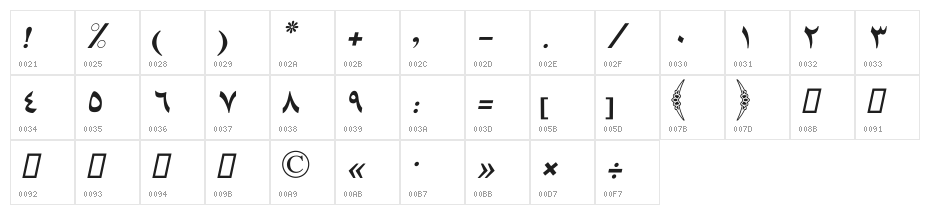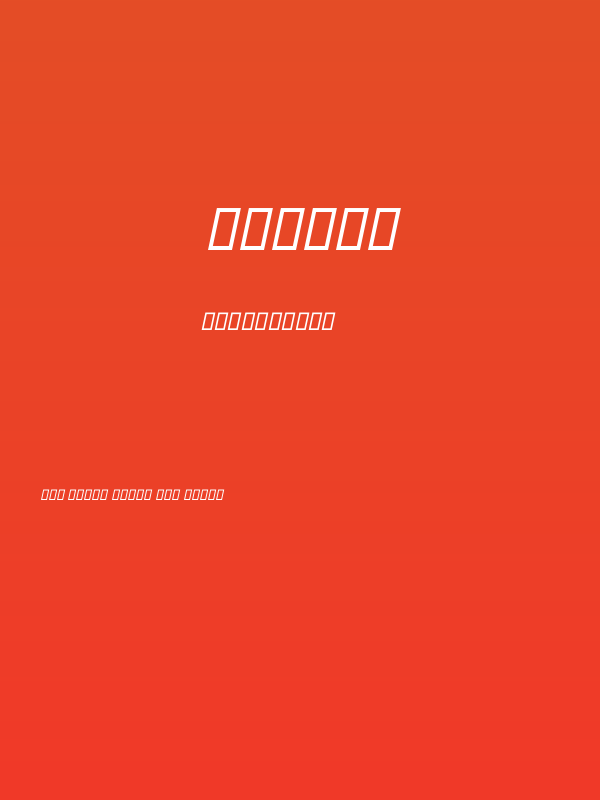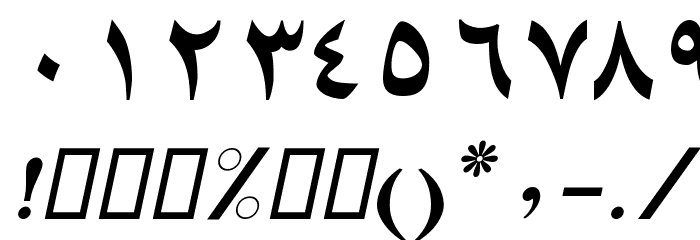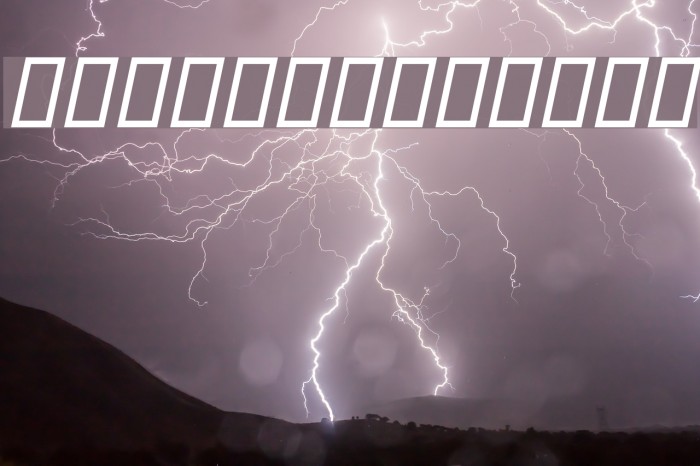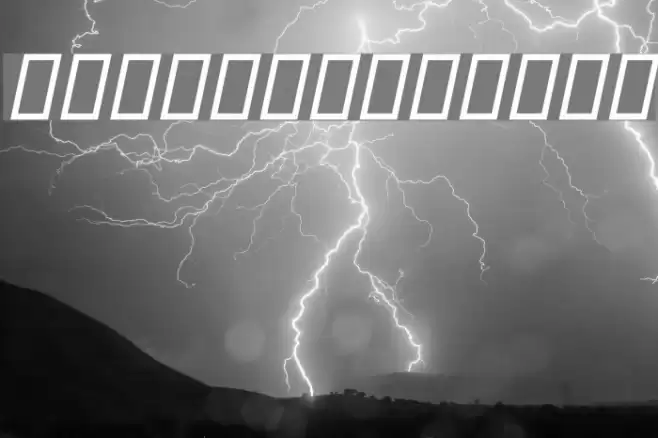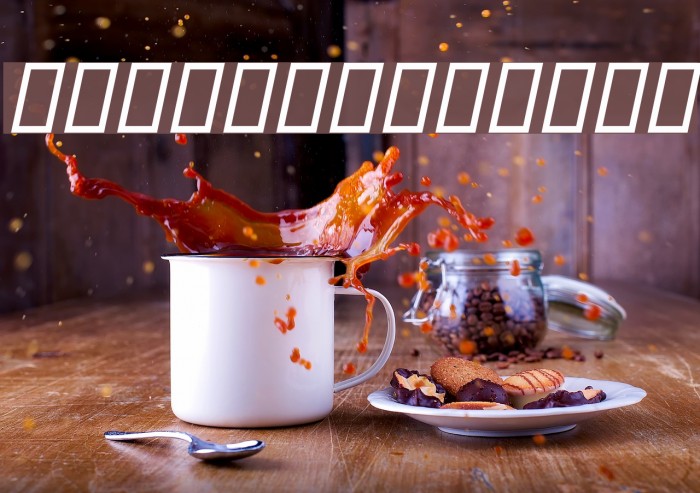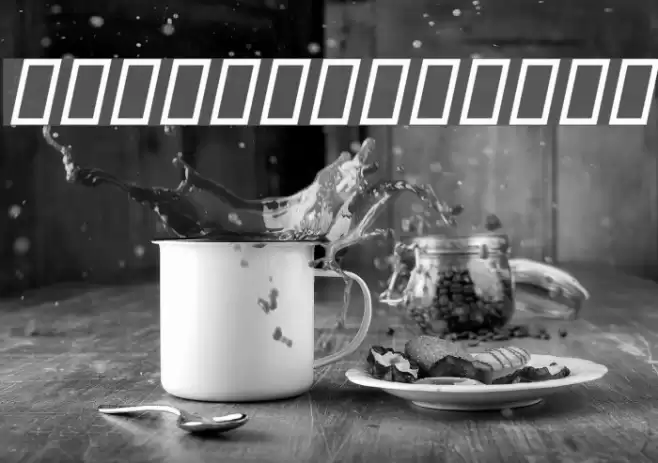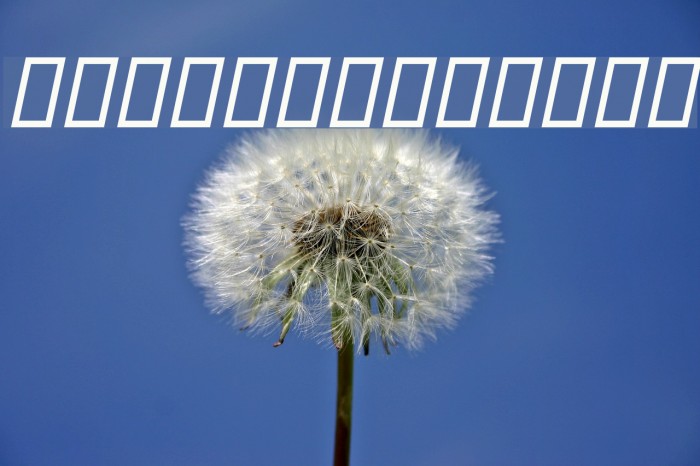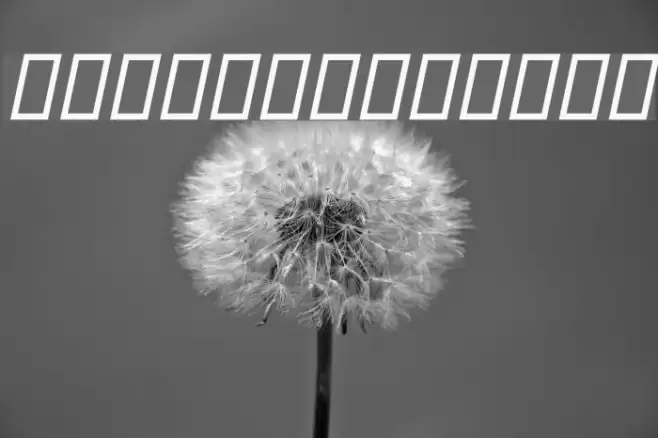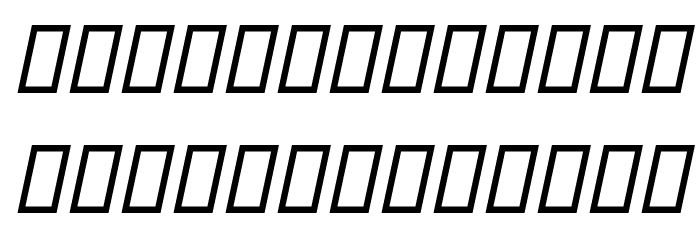
Mazaar Font
گالری فانت فارسی پژوهش آريانا - only compatible with Farsi and Arabic
| इटैलिक | Yes |
| कंट्रास्ट | High |
| समग्र शैली | Modern, Decorative |
| उपयोग का मामला | Logos, Headlines, Digital Art |
| सुझाए गए प्रोजेक्ट | Ideal for futuristic designs, tech branding, digital art projects, and innovative advertising campaigns. |